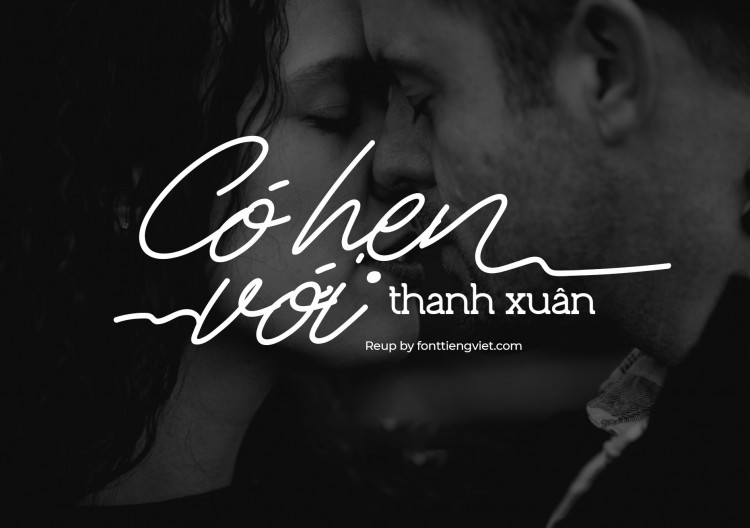
Giới thiệu về Font việt hóa MJ Amsterdam
Trong thế giới thiết kế đồ họa hiện đại, việc lựa chọn một Font Chữ phù hợp đóng vai trò quyết định đến tính thẩm mỹ của sản phẩm. Font việt hóa MJ Amsterdam là một trong những bộ phông chữ mang phong cách chữ viết tay (handwriting) đầy cá tính và nghệ thuật. Với các đường nét thanh mảnh nhưng không kém phần mạnh mẽ, bộ font này mô phỏng chân thực nét bút ký phóng khoáng, giúp các tác phẩm trở nên gần gũi và có hồn hơn. Đặc biệt, phiên bản Font việt hóa MJ Amsterdam đã được tối ưu hóa đầy đủ dấu tiếng Việt, giúp các bạn học sinh và thầy cô dễ dàng sử dụng trong học tập cũng như trình bày bài giảng.
Tại sao nên chọn Font việt hóa MJ Amsterdam?
Bộ font này sở hữu những ưu điểm vượt trội về mặt hiển thị. Các ký tự được thiết kế với độ kết nối tự nhiên, tạo cảm giác như được viết trực tiếp trên giấy. Điều này cực kỳ phù hợp cho các dự án thiết kế thiệp mời, bìa sách, hoặc các slide thuyết trình cần sự độc đáo. Font việt hóa MJ Amsterdam không chỉ đẹp mắt mà còn đảm bảo khả năng đọc tốt trên cả thiết bị di động và máy tính, mang lại trải nghiệm thị giác ấn tượng cho người xem.
Ứng dụng thực tế của Font việt hóa MJ Amsterdam
Nhờ phong cách trẻ trung và hiện đại, Font việt hóa MJ Amsterdam thường xuyên được ưu tiên trong các dự án sáng tạo nội dung số. Bạn có thể dùng font này để làm tiêu đề video, thiết kế ảnh trích dẫn (quote) trên mạng xã hội hoặc trang trí các ấn phẩm trường học. Việc sử dụng Font việt hóa MJ Amsterdam đúng cách sẽ giúp thông điệp của bạn trở nên nổi bật và thu hút sự chú ý của mọi người ngay từ cái nhìn đầu tiên.